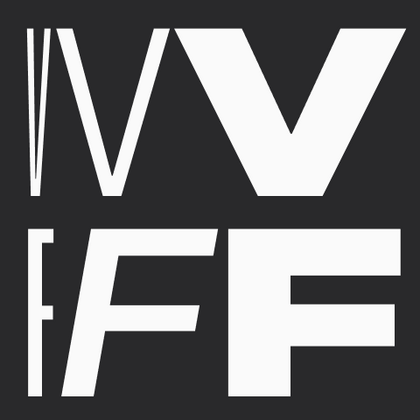
Вариативные шрифты
Вариативные шрифты стали прорывом в шрифтовых технологиях! Теперь шрифтовой дизайнер может зашить в один шрифтовой файл несколько шрифтовых файлов и с помощью ползунков вариативности в режиме реального времени изменять настройки вариации шрифта. Вариативность может быть любой, начиная от традиционной вариативности по ширине, весу или наклону шрифта и заканчивая вариативностью, непосредственно влияющей на визуальный облик шрифта. Ещё одно преимущество вариативного формата шрифта, особенно если вы работаете с веб-типографикой, — небольшой вес шрифтового файла, по сравнению с весом традиционного шрифтового семейства.
В библиотеку TypeType уже входит 29 вариативных шрифтов на любой вкус и под любую задачу. Вариативные шрифты из библиотеки TypeType можно разделить на четыре большие группы:
• ультимативные вариативные рабочие лошадки с тремя осями вариативности;
• шрифты с двумя осями вариативности;
• простые вариативные шрифты с 1 осью вариативности;
• вариативные шрифты, влияющие непосредственно на дизайн шрифта.
К первой группе можно отнести ТТ Коммонс Про (TT Commons™ Pro) вариативный, ТТ Лейкс Нью (TT Lakes Neue) вариативный, ТТ Октосквэрс (TT Octosquares) вариативный, ТТ Супермолот Нью (TT Supermolot Neue) вариативный. У всех этих шрифтов вариативность регулируется по трём осям (толщина, ширина и наклон), благодаря чему пользователь получает широкую палитру выбора и возможность настроить ползунки так, чтобы создать уникальное сочетание.
Ко второй группе относятся шрифты с двумя осями вариативности, такие как ТТ Ховс Про (TT Hoves Pro) вариативный, ТТ Форс (TT Fors) вариативный и ТТ Отонамус (TT Autonomous) вариативный. В отличие от первой группы, эти шрифты не позволяют работать с осью ширины, так как имеют только одну дефолтную ширину, но при этом они дают полную свободу (ограниченную лишь крайними значениями) в настройке толщины шрифта, его наклона или комбинации обоих значений.
К третьей группе шрифтов относятся шрифты с одной осью вариативности. Для каждой из осей есть отдельный шрифтовой файл. К таким шрифтам относятся ТТ Глобс (TT Globs) вариативный, ТТ Отонамус Моно (TT Autonomous Mono) вариативный, ТТ Рамильяс (TT Ramillas) вариативный, ТТ Ранс (TT Runs) вариативный, ТТ Интерфейзис Про (TT Interphases Pro) вариативный, ТТ Интерфейзис Моно (TT Interphases Mono) вариативный, ТТ Трейлерс (TT Trailers) вариативный, ТТ Нормс Про (TT Norms® Pro) вариативный, ТТ Фирс Нью (TT Firs Neue) вариативный. При работе со шрифтами этой группы у вас есть определённая свобода в выборе одного из параметров (ширины или толщины), что в свою очередь позволяет настроить шрифт под ваши задачи.
Самой необычной является четвёртая группа вариативных шрифтов от TypeType, к которой относятся ТТ Элиенц (TT Alientz), ТТ Франтц (TT Frantz) и ТТ Гикетт (TT Geekette). Основное отличие этой группы заключается в том, что вариативность влияет непосредственно на дизайн самого шрифта. Например, в ТТ Франтц с помощью ползунка вариативности можно поменять среднюю линию шрифта: от очень высокого модернового вида до низкого и немного авангардного. Вариативность в ТТ Элиенц позволяет трансформировать стиль шрифта от яркого и акцидентного гротеска в сторону очень колючей и характерной антиквы. А шрифт ТТ Гикетт может трансформироваться от монолинейного брускового шрифта в пластичный брусковый с обратным контрастом.
TT Polihaus — экспериментальный гротеск, который на первый взгляд кажется обычным, а затем разбирается на части, превращаясь в трафаретный узор.
TT Odellia — старостильная антиква с современным рисунком, вдохновлённая венецианскими шрифтами и классической музыкой.
TT Nooks Serif — акцидентная новостильная антиква с лёгким налётом эгоцентричности. У неё острый и твёрдый, при этом элегантный и статный характер.
TT Chocolates — изящный гуманистический гротеск сo сбалансированными пропорциями, близкими к классическим. Шрифт с приятным дружелюбным характером, который интуитивно воспринимается как что-то знакомое.
TT Nooks Script — шрифт с уникальным рисунком, который не имеет прямых аналогов.
TT Supermolot Neue — технологичный модульный гротеск с футуристическим настроением и мощным функционалом. Яркость его характера сочетается с универсальностью применения.
TT Norms® Pro — один из самых востребованных шрифтов студии, выбор известных мировых брендов. Более трёх переизданий за семь лет, первые строчки на MyFonts, десятки кастомизаций. Это «рабочая лошадка», которая станет незаменимой базой любой шрифтовой коллекции.
TT Commons™ Pro — один из самых востребованных шрифтов студии. Сфера его применения практически безгранична! Беспроигрышный вариант для тех, кто ищет стильный и функциональный базовый шрифт для любых проектов.
TT Hoves Pro — скандинавский гротеск с нейтральным, но в то же время узнаваемым характером. Это удобный и функциональный, при этом стильный и эстетичный инструмент для дизайнеров. Такой шрифт позволит вам решать множество разноплановых задач!
TT Ricordi Greto — неконтрастный флорентийский гротеск с динамичными пропорциями. Это единственный гротеск среди антикв в коллекции TT Ricordi, при этом в нем сохранились едва заметные засечки, отсылающие к прототипу.
TT Firs Neue — скандинавский гротеск, сочетающий выразительные графические элементы с универсальностью использования. Мы проанализировали каждый контур и графический элемент. Пересобрали шрифт заново, чтобы сохранить лучшее и исправить необходимое.